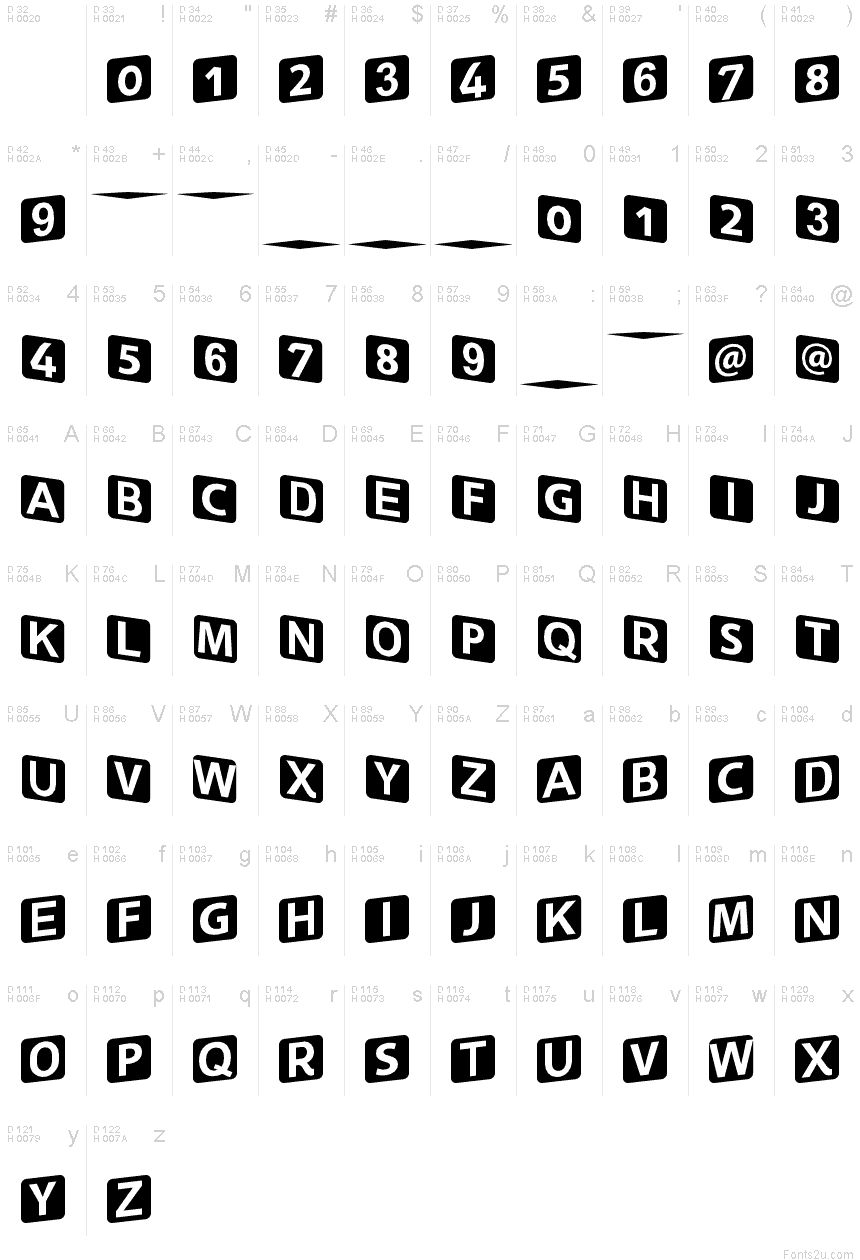
square kids
Es una fuente creada para dar la ilusin de que es un dado didactico, creado para un logo de una guarderia
It is a font created to give the illusion that it is a dice didactic, a logo created for a nursery